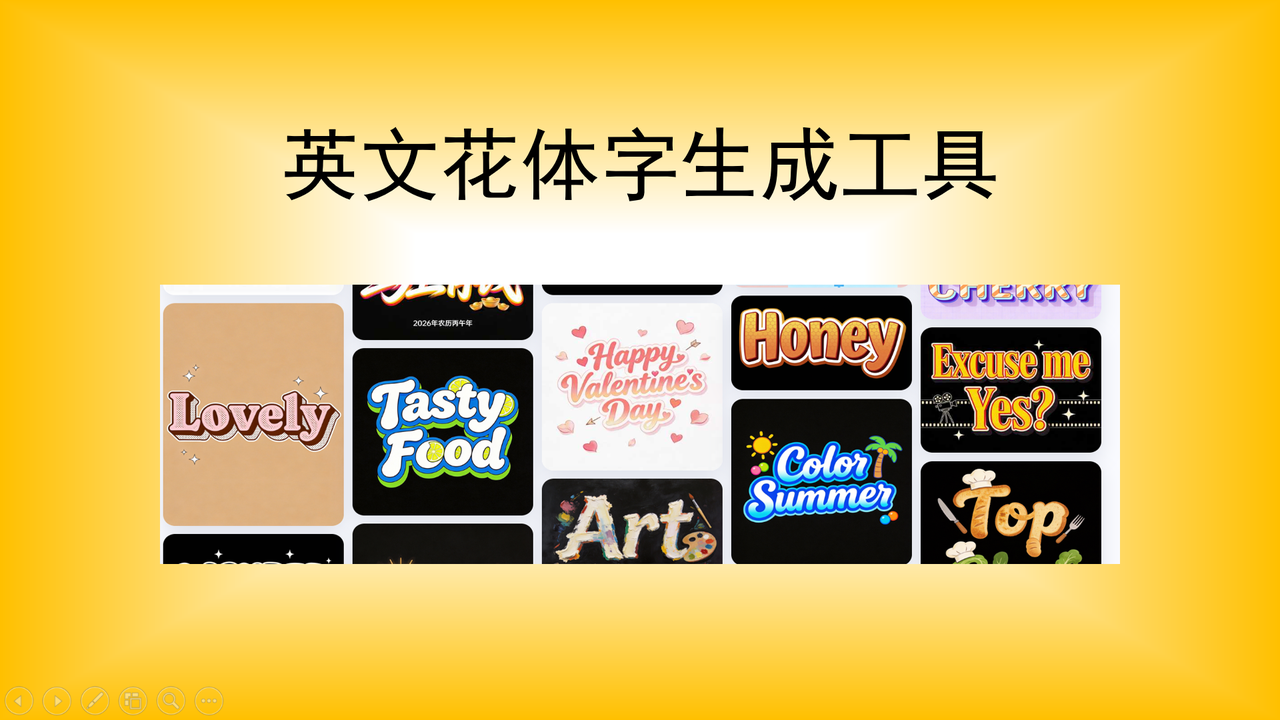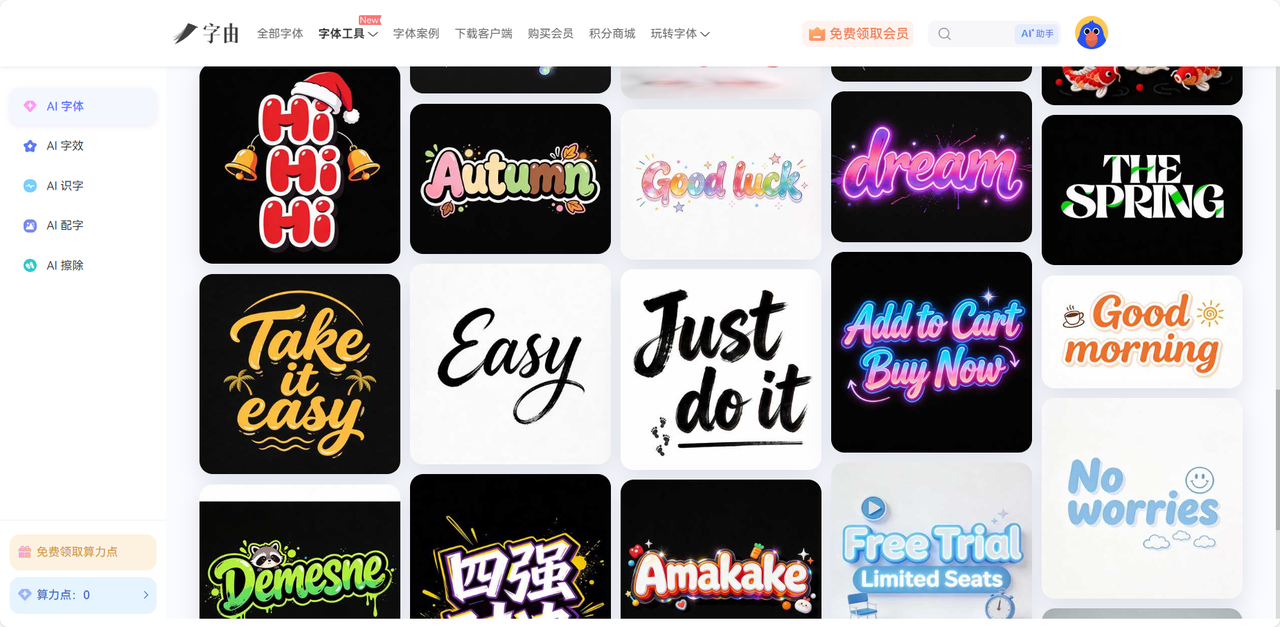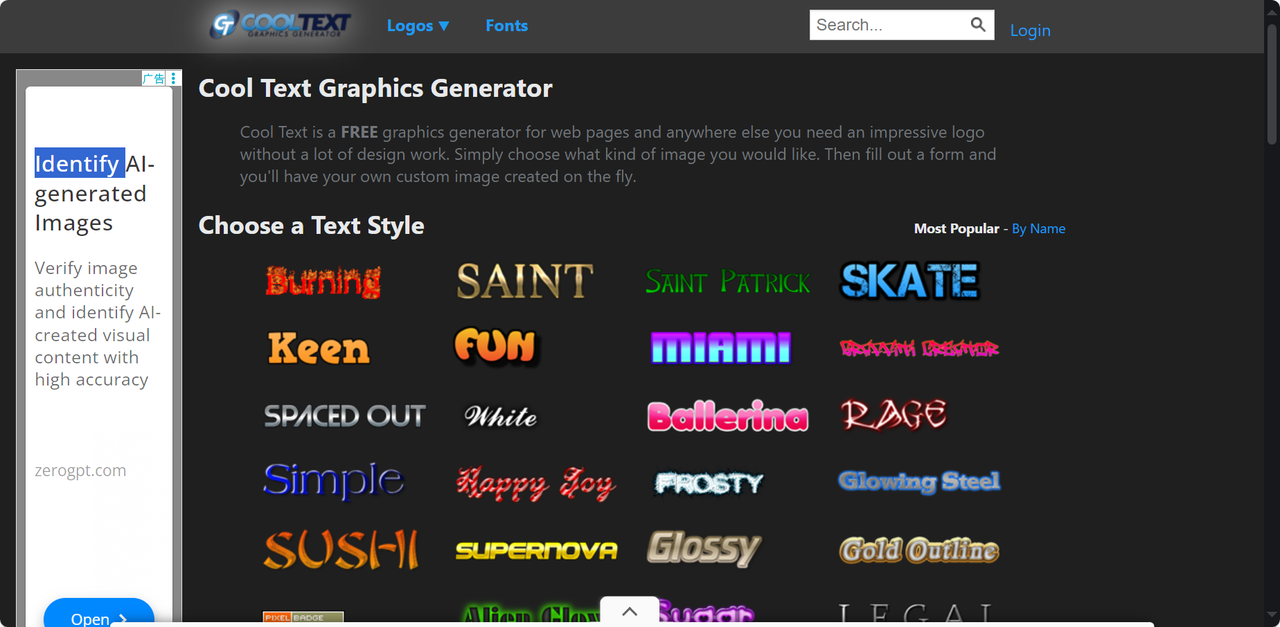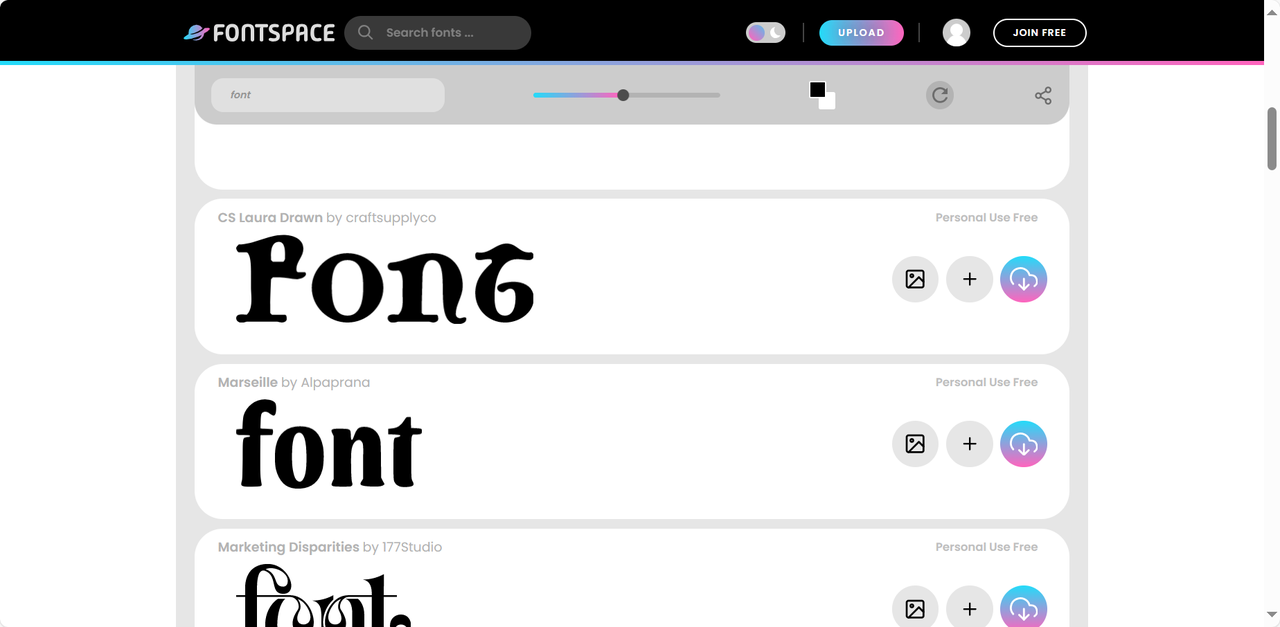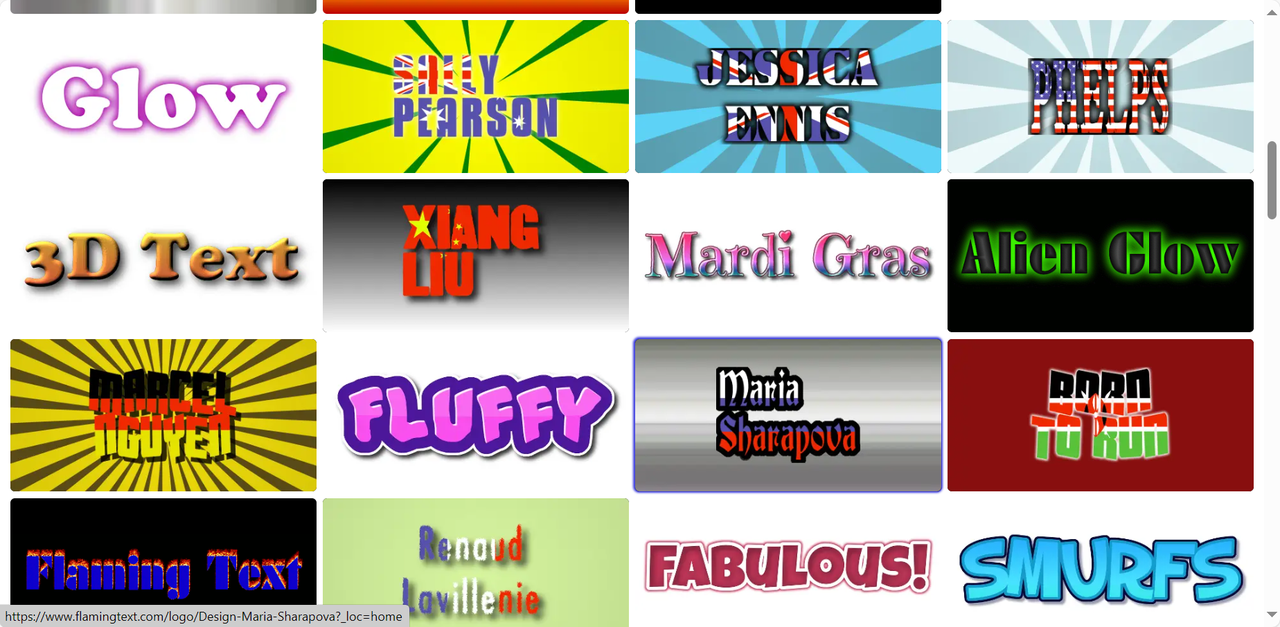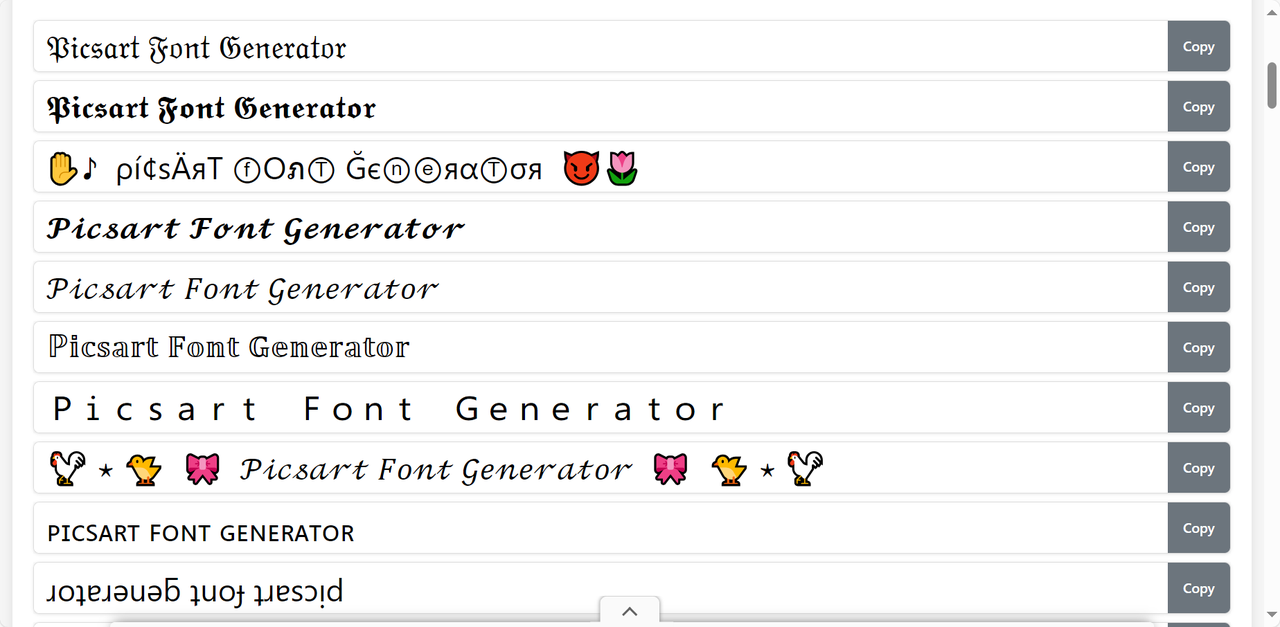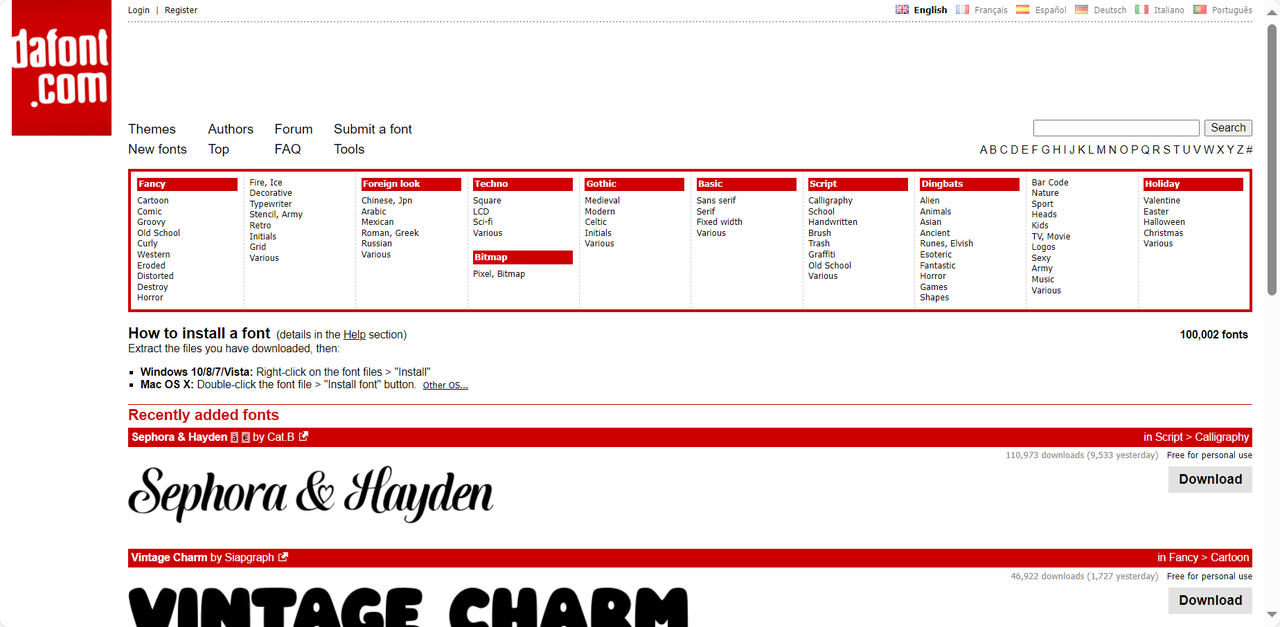
英文花体字在线生成,这些工具赶快收藏!
觉得自己的海报不够精致,不够吸引人?可以加入一些英文花体字,增强页面的层次感和艺术感,花体字的出现也会很大程度上吸引大众的视线。手动设计花体字需要一定的设计经验和能力,对于我们这些新手设计师来说,优质的英文花体字工具可以快速生成精美字体,无需过硬的专业技能。本文会给大家推荐 6 款英文花体字生成工具,可以用于品牌包装、海报标题、婚礼请柬等装饰性设计,也可以用于手账、贺卡、礼物等艺术类设计。希望在这些工具的帮助下,让更多人可以获得优美的英文花体字。
一、字由
字由是我首选推荐的字体工具,它不仅仅可以在线生成花体字,还是一个全方位、多功能的字体管理工具,不管是个人还是企业使用,它都是非常好的选择。着重来说一下我对它的体验感吧~想要生成英文花体字,其实只需要进入【 AI字体 】功能,按照场景或风格筛选想要英文字体,字由给你提供了超多选择,一键生成同款就可以搞定啦!而且下载后的字体都是 PNG 格式,方便你继续在其他设计软件内完成设计。
二、Cool Text
Cool Text 主要适用于网页设计,是一款免费的图形生成器。它一共多种预设好的花体特效,例如霓虹、复古、荧光、烫金等,在线即可生成英文花体字,新手 30s 之内就能获得酷炫花体标题。操作非常简单,选择特效模板,输入想要的英文内容,自定义调整颜色、字间距、阴影效果、字体大小就可以完成啦。Cool Text 生成的花体字支持 PNG/JPEG 下载,且没有水印,用户直接就可以用。
三、FontSpace
FontSpace 是很多国际设计师信赖的英文花体字在线生成平台,拥有 160,000+ 免费字体,适配各种类型的设计项目。如果喜欢涂鸦风格的设计师们,可以尝试一下这个工具,它专门给涂鸦类字体设置了分区,每一款涂鸦英文花字分效果都很逼真,简直就和在城市街头可以经常见到的喷涂字体一模一样。
FontSpace 还支持在线实时预览,输入英文文本可以获取合适的花体效果。每款字体都清晰标注了授权形式,可直接下载为 PNG 透明背景图,用于 PS、Figma、AI 常用设计软件都是非常方便的哦。
四、Flaming Text
Flaming Text 是进阶版的英文花体字在线生成工具,内置200+免费花体字模板,支持纹理叠加、渐变等多种风格,适合制作复杂类的花体标题。最值得一提的就是它拥有图层编辑功能,你可以在线编辑花体字,对于设计者来说自由度很高,接近 PS 带来的体验。不过一些复杂高级的素材需要付费,如果追求更高质量的英文花体字,或许可以换一个工具。
Flaming Text 生成的英文花体字非常适合英语电影或动画片的片头名称,因为它的大部分花体字都是自带酷炫背景的,且配色鲜明,一秒可以吸引大众的视线。
五、PicsArt Online Fonts
PicsArt Online Fonts 相比于网页端,更适合用于移动端,可以让你随时随地生成想要的花体字。个人认为,它的英文花体字适合用于社交媒体帖子、个人签名、手机端海报,为你创作出惊艳且美观的文字设计。PicsArt Online Fonts 内置丰富字体库,其中手写艺术字居多,而且在生成字体的过程中可以选择文字特效、文字颜色、 贴纸、图片等等,有效增强花体字的视觉吸引力。最关键的是,它可以在线创建圆形、扭曲、波形字体,用户选择度非常高。
虽然是国外的工具,全英文页面,但是操作非常简单。只需要打开 PicsArt Online Fonts 选择合适的图片或背景,在文本框内输入你想要的内容,再挑选一个心仪的花体字模板,使用它的内置功能在线编辑花体字,最后导出设计或者可以直接分享到你喜欢的平台。
六、DaFont
DaFont 想必大家都不陌生,是一个免费的字体资源平台,覆盖全球化用户。它同样提供大量的免费花体字,免费商用字体含量占比很高,还支持用户自定义设计。我认为 DaFont 最大的优势就是关于字体分类,类别细致且清晰,它按照字体风格、字体用途、字体类型等多方面进行划分,帮助大家快速定义想要的字体。
英文花体字的生成就是这么简单,有了这些工具的帮助,你也可以拥有优质的英文花体字。就我个人的体验感来说,字由是用起来最顺手的,首先因为它是全中文的平台,我们可以清晰的知道每个功能如何去选择,如何使用;其次,字由的花体字资源非常丰富多样,还有大量免费商用的字体,对于不想花费太多金钱做设计的朋友来说是绝佳选择。快去亲自体验一下吧,让英文花体字帮你提升作品的质感!